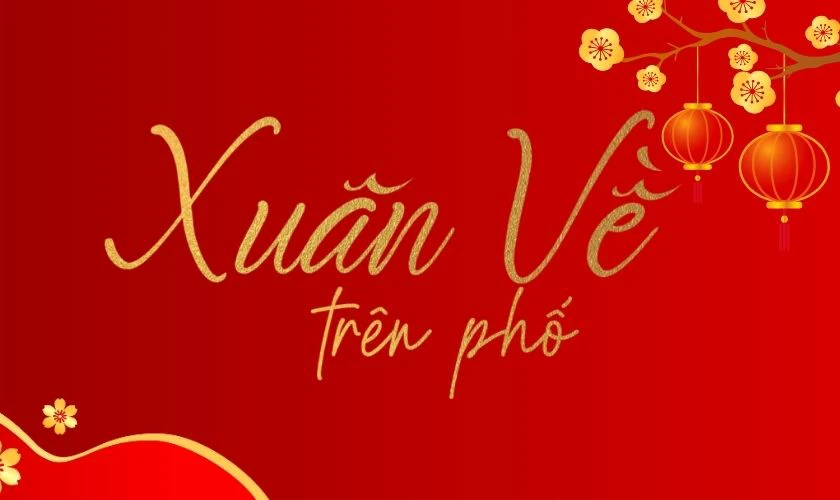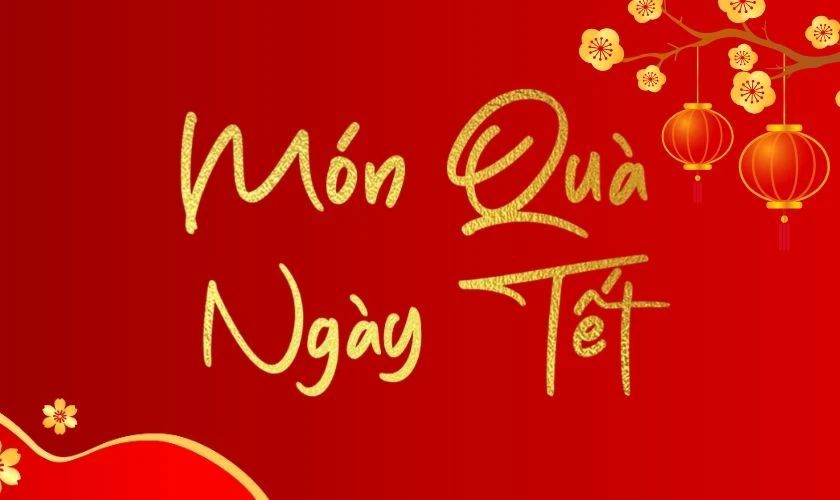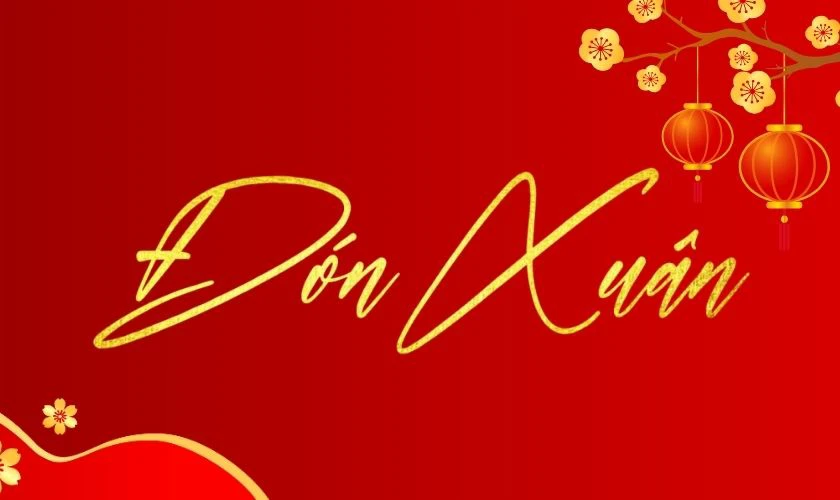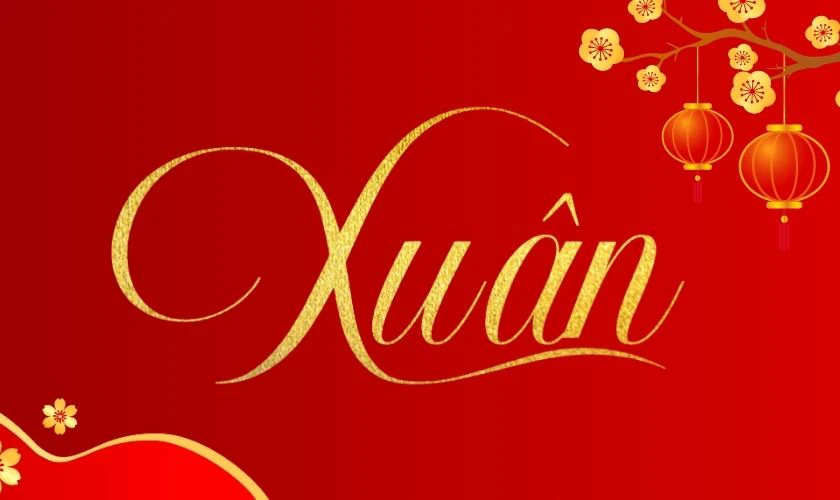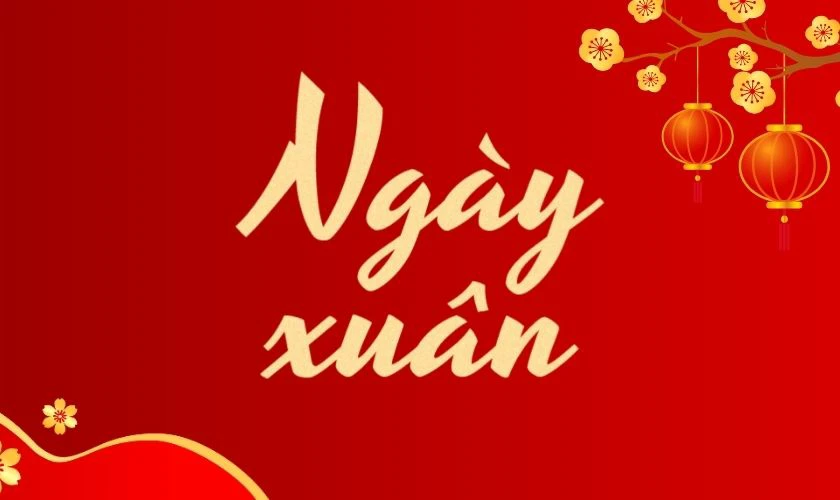
95+ font chữ Tết Việt hóa miễn phí, đẹp, độc đáo 2026
Font chữ Tết phù hợp là yếu tố quan trọng giúp thiết kế trở nên nổi bật và truyền tải trọn vẹn thông điệp ngày đầu năm. Lựa chọn đúng font chữ phù hợp sẽ giúp poster, banner hoặc ấn phẩm ngày Tết trở nên ấn tượng và thu hút hơn. Hãy cùng chúng tôi khám phá ngay 95+ font chữ Tết Việt hóa đẹp, miễn phí ngay trong bài viết dưới đây!
Điểm danh top font chữ Tết đẹp và miễn phí 2026, bạn có thể sử dụng những font chữ sau đây để giúp những hình ảnh của mình trở nên sinh động và nổi bật hơn.
Font Rukola nổi bật với thiết kế độc đáo, các đường nét cách điệu sáng tạo, thích hợp cho những ai muốn tạo dấu ấn riêng trong các thiết kế bao lì xì, poster hay quà tặng ngày Tết.
UTM Spring là font chữ thư pháp với nét bút nghệ thuật, mang đậm tính truyền thống nhưng không kém phần sáng tạo. Font này rất phù hợp để tạo các thiết kế đậm chất ngày Tết như thiệp chúc mừng, túi quà hoặc lịch xuân.
Font chữ ngày Tết cổ truyền là lựa chọn lý tưởng để thể hiện nét đẹp văn hóa Việt Nam trong các thiết kế mùa Tết. Với các đường nét uyển chuyển, mềm mại, font chữ này thường được dùng trong thiết kế bao lì xì, thiệp chúc mừng hoặc trang trí lịch Tết.
TH Colombo Sans là một font chữ mang phong cách hoài cổ với các đường nét đơn giản nhưng đầy ấn tượng. Font này phù hợp cho các thiết kế mang hơi hướng retro như poster, banner hoặc áp phích quảng cáo mùa Tết. Sự kết hợp giữa nét cổ điển và hiện đại giúp font này trở thành lựa chọn phổ biến cho các sản phẩm sáng tạo.
Font chữ TLM Bladrimmer sở hữu phong cách cổ trang độc đáo, mang lại vẻ đẹp sang trọng và đậm chất nghệ thuật. Với các chi tiết tinh xảo và đường nét sắc sảo, font chữ này rất phù hợp để thiết kế poster, thiệp mời hoặc các sản phẩm liên quan đến ngày Tết mang hơi hướng truyền thống.
Font chữ 1FTV VIP Shalyne mang phong cách đẹp mắt, được thiết kế tỉ mỉ dành riêng cho dịp Tết. Font sở hữu nét chữ nổi bật, mềm mại và đầy cá tính giúp thiết kế trở nên thu hút và ấn tượng hơn, đặc biệt phù hợp với không khí xuân tràn đầy rực rỡ và năng lượng.
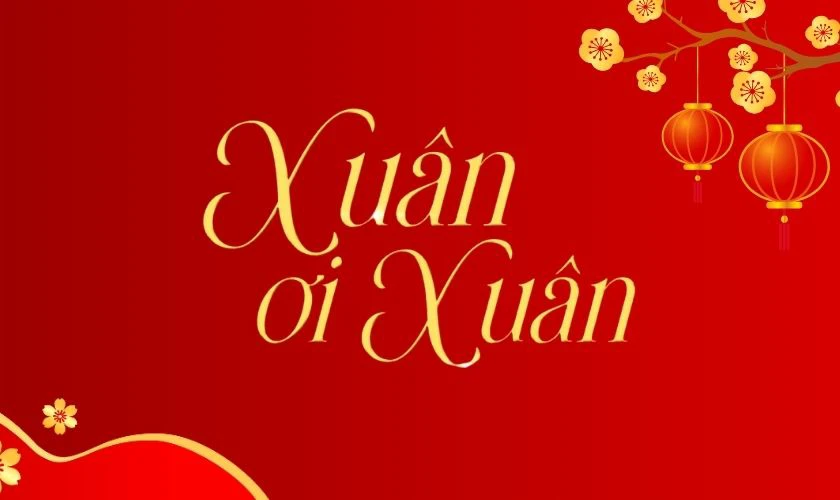
Font chữ Tết Zoika là mẫu phông được Việt hóa theo phong cách hiện đại. Các đường nét font chữ mềm mại và đầy tính thẩm mỹ, dễ dàng sử dụng trong các thiết kế Tết và dự án đầu năm. Font chữ Zoika có thể sử dụng để làm tiêu đề, logo, poster, thiệp mừng hoặc nhiều ấn phẩm khác nhau.
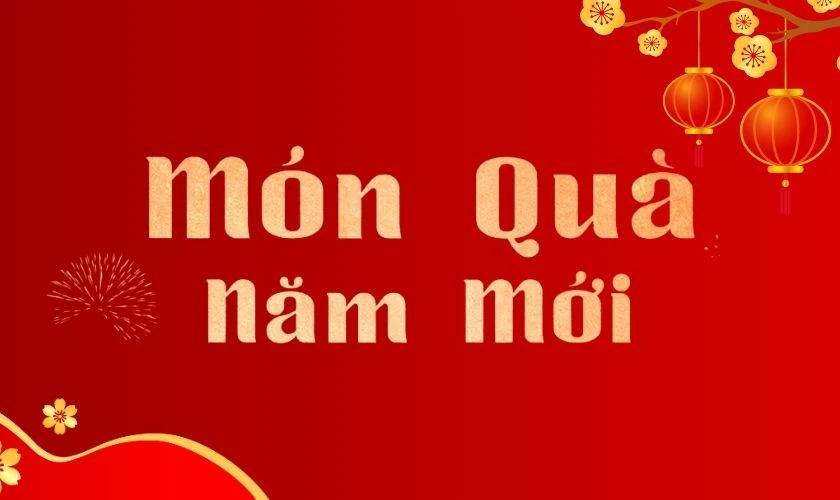
Font chữ Medino sở hữu thiết kế tinh tế và đầy sang trọng, phù hợp để tạo điểm nhấn cho các ấn phẩm dịp Tết. Đặc trưng của font chữ là nét chữ to, rõ ràng, cân đối thu hút ánh nhìn.
Đây là mẫu font chữ mang phong cách nghệ thuật viết tay thanh lịch pha chút cổ điển. Mẫu font chữ này đem đến cảm giác nghệ thuật tự nhiên và mềm mại cho nội dung, phù hợp làm tiêu đề trong các ấn phẩm Tết. Với cấu trúc chữ thanh thoát, hỗ trợ tiếng Việt và hiệu ứng tinh tế, font Peristiwa là sự lựa chọn phù hợp không nên bỏ qua trong dịp Tết.
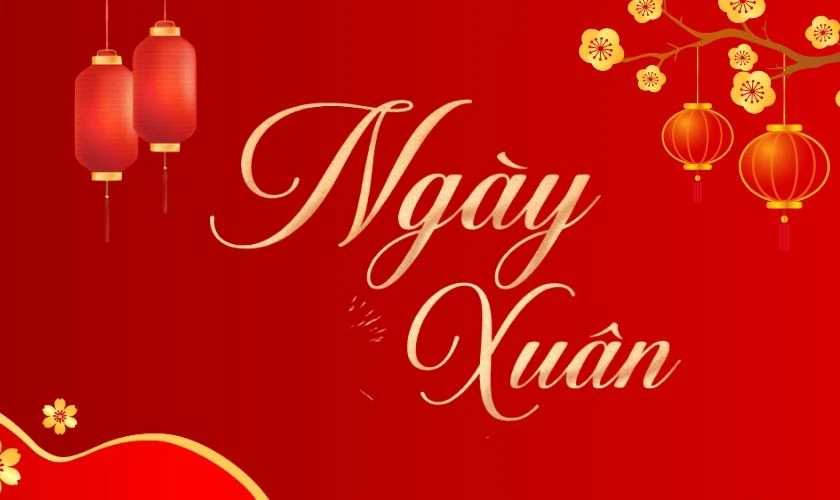
Sau đây các font chữ Tết Việt hoá đầy đủ tiếng Việt mà bạn có thể sử dụng trong các thiết kế hình ảnh Tết của mình.
Font chữ TH Hidayat được thiết kế theo phong cách cổ điển, với những nét uốn lượn đầy nghệ thuật và mang đậm hơi thở cổ trang. Đây là lựa chọn lý tưởng cho các tác phẩm đậm chất truyền thống, chẳng hạn như tranh ảnh, sách sử hoặc thiệp chúc mang đậm văn hóa Việt.
Stampa là một font chữ bao cấp Việt hóa, nổi bật với kiểu dáng vuông vắn và đường nét đậm. Font chữ này tạo cảm giác mạnh mẽ và đặc trưng của những năm 70 - 80. Với khả năng gây ấn tượng ngay từ cái nhìn đầu tiên, Stampa thường được sử dụng trong các thiết kế quảng cáo và truyền thông mang tính hoài cổ.
Thư pháp Giao Long sở hữu các nét chữ đậm và dày dặn, mang lại cảm giác mạnh mẽ và trang trọng. Font này phù hợp để sử dụng trong các thiết kế banner Tết hoặc thiệp chúc mừng mang phong cách cổ truyền.
Font chữ Glamora sở hữu đường nét tinh xảo, các đường nét được chăm chút kỹ lưỡng, chuyên nghiệp. Kiểu chữ này mang đến cảm giác mềm mại và đầy thu hút, nổi bật để làm nội dung trong các ấn phẩm đầu năm.
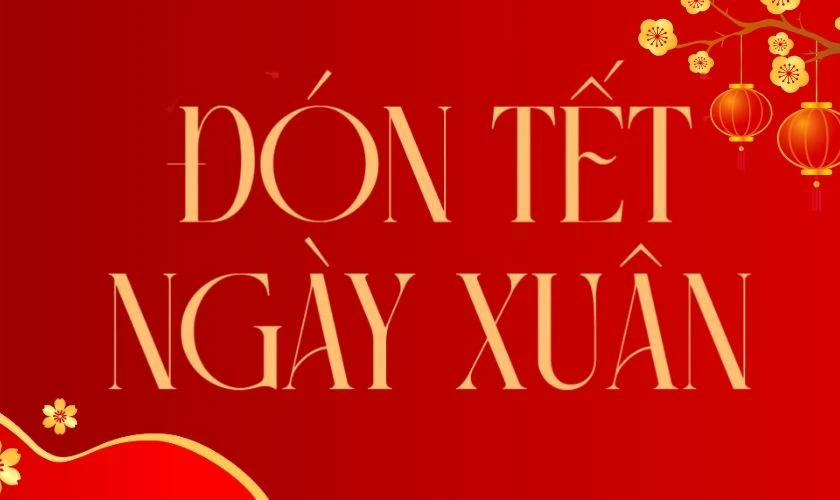
Font chữ VIP Angrela Display là mẫu chữ đậm nét, thanh thoát với phần đuôi chữ được cách điệu mềm mại. Đây là mẫu chữ phù hợp để tạo điểm nhấn cho phần tiêu đề, tiêu đề phụ trong các ấn phẩm truyền thông.
Russo One là mẫu font chữ sở hữu hình thái chữ đậm, to, mang đến cảm giác mạnh mẽ có phần truyền thống. Với chiều sâu hình khối rõ ràng và hỗ trợ đầy đủ tiếng Việt, kiểu chữ giúp làm nổi bật tiêu đề và nội dung trong các thiết kế đầu năm, đảm bảo thu hút người nhìn và lan tỏa không khí Tết.
Font Relationship Of Mélodrame – Tết mang phong cách mềm mại với các đường nét uyển chuyển tinh tế, tạo cảm giác nhẹ nhàng và bay bổng. Mẫu chữ này giúp tăng tính biểu cảm cho từng câu chữ. Phù hợp làm nổi bật nội dung cần tập trung vào chiều sâu cảm xúc trong các ấn phẩm đầu năm.
Đây là kiểu chữ sở hữu các đường nét thanh lịch, mang hơi hướng cổ điển tạo nên cảm giác nhẹ nhàng và đầy ấn tượng. Kiểu chữ này được thiết kế có phần cao ráo, thanh mảnh, mang đến chiều sâu thị giác cho từng câu chữ, giúp truyền tải nội dung tốt hơn.